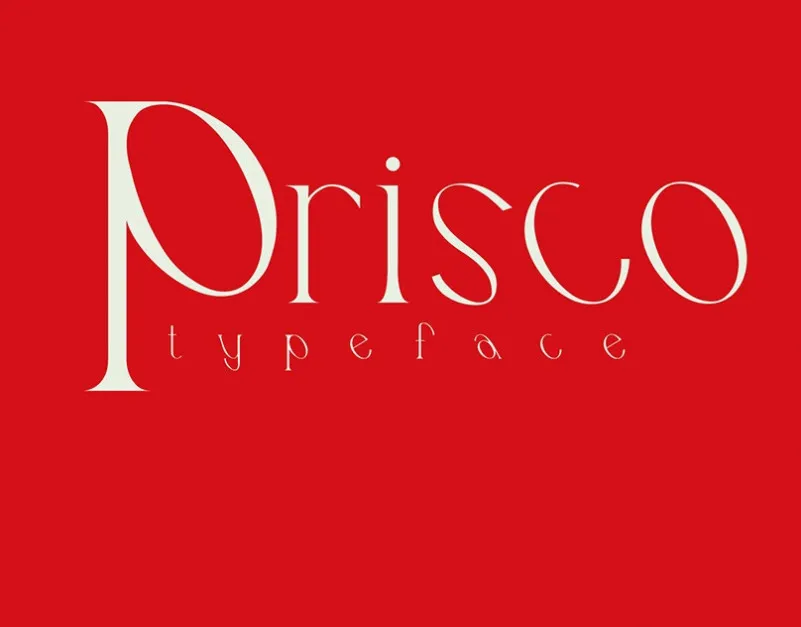
A Prisco Font é uma elegante serif font exclusiva criada pela Coral Ruiz. Ideal para aqueles que buscam design moderno e minimalista com um toque sofisticado e sofisticado, a Prisco pode ser usada em uma ampla variedade de materiais gráficos. Perfeita para criação de logotipos, materiais de identidade visual corporativa, cartões de visita, cupons de presente, camisetas personalizadas, capas, miniaturas, impressão, posters, fotografia e citações. Suavizando as linhas com seu estilo elegante e único, a Prisco é uma ótima opção para quem procura um equilíbrio entre modernidade e sofisticação em seus projetos gráficos.